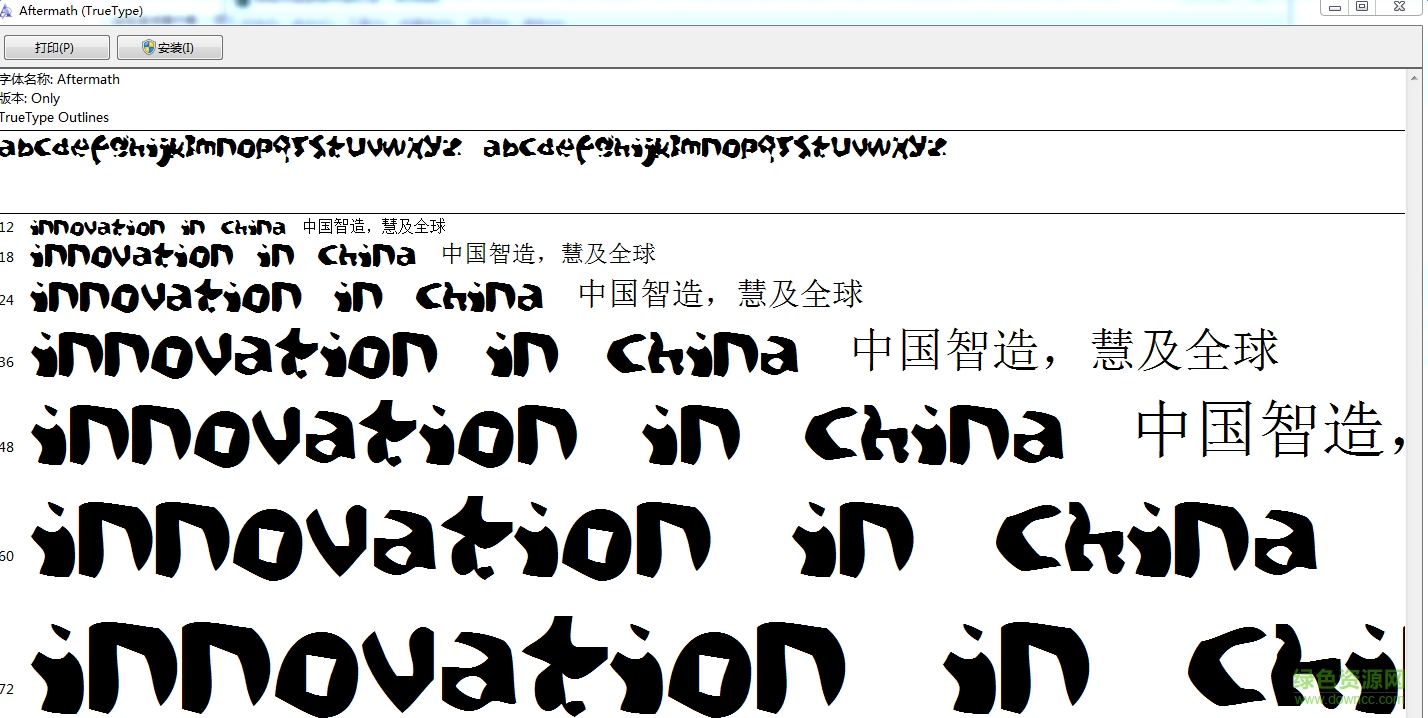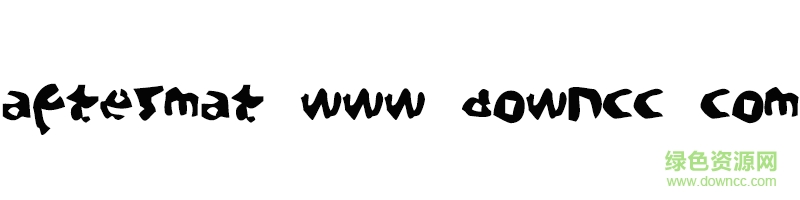
Aftermat
Aftermat字體是一款A(yù)ftermat風(fēng)格英文字體軟件,Aftermat風(fēng)格的字體給人非常潦草的感覺(jué),深受廣大年輕人的喜愛(ài),還有更多好看字體盡情期待,歡迎到綠色資源網(wǎng)下載體驗(yàn)!
Aftermat介紹
Aftermat是一款A(yù)ftermat風(fēng)格英文字體,字體效果比較潦草,喜歡英文體字的朋友可以下載使用看看效果如何。
Aftermat字體